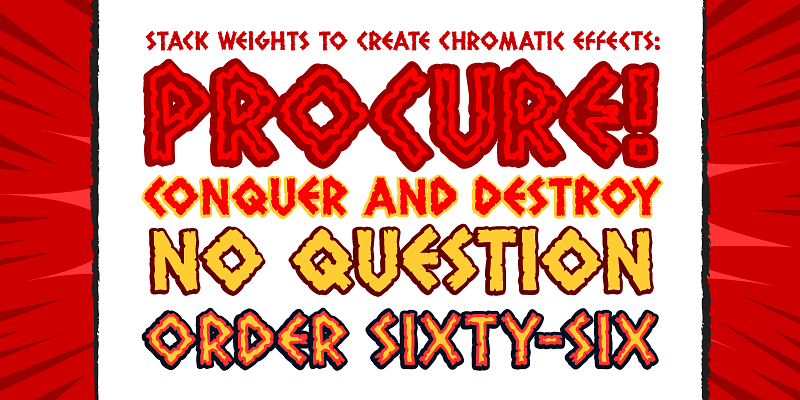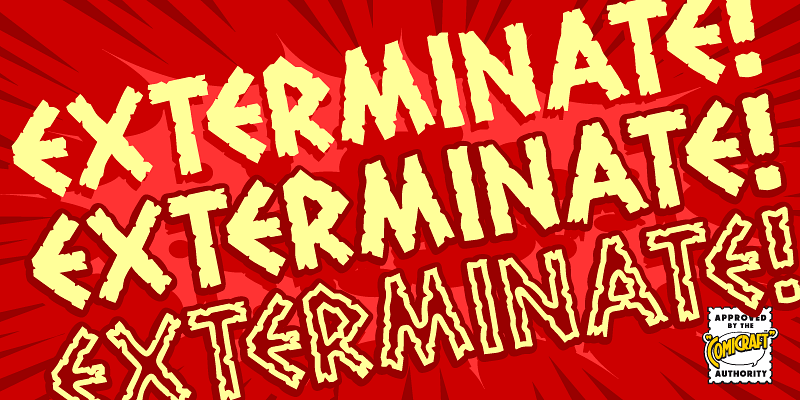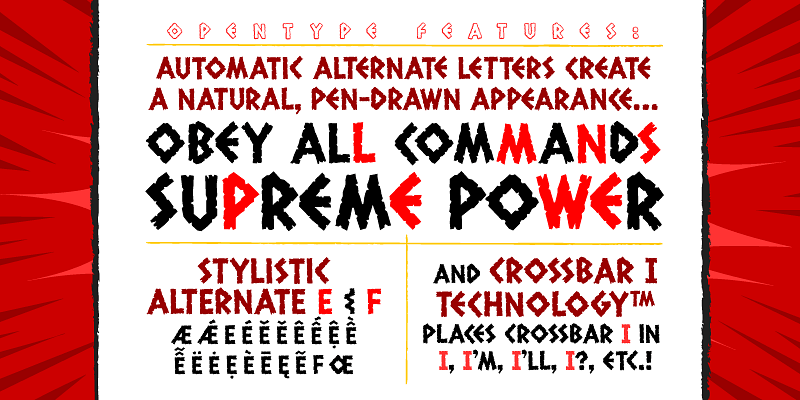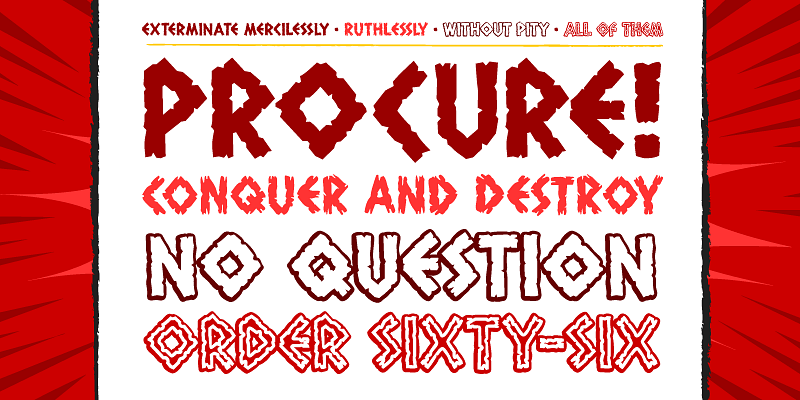
世界最高のコミックフォントです。何千冊ものコミックブックに忠実に文字を提供してきた Comicraft の Fearless Fonts は、ビデオゲームやテレビ番組、映画のタイトルなど、楽しくて生き生きとしたフォントが必要とされる場所で、人々を救ってきました。
1992 年、Richard Starkings と John Roshell の Dynamic Duo と、その Fearless Fleet of Font Finaglers が、コミック本やテレビ、ビデオゲーム業界に独自のデザインと細かい文字を提供し始めたことが、コミック本のレタリングにコンピューターを使用した先駆けとなりました。
自らが作ったものではない世界に閉じ込められた Comicraft の Fearless Fonts が、間一髪で救いに来てくれることでしょう